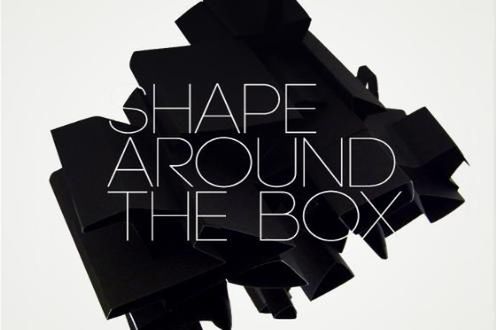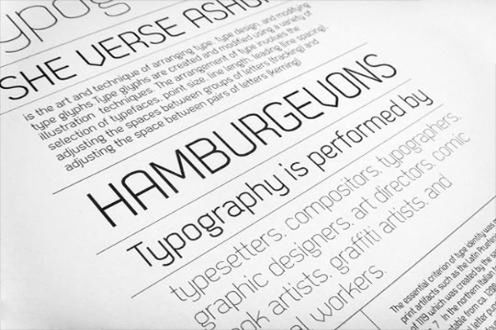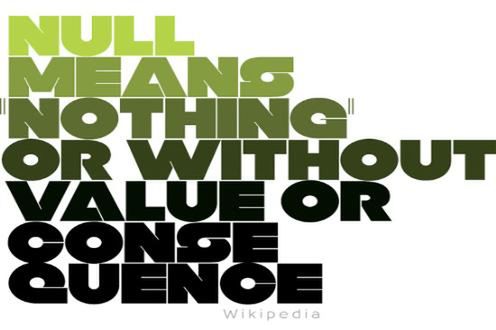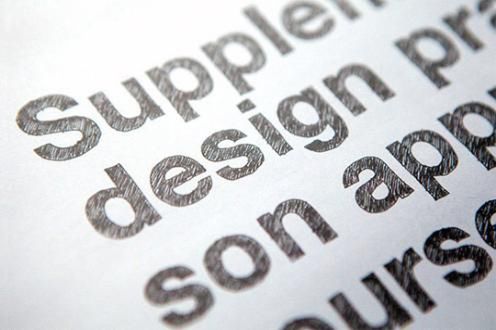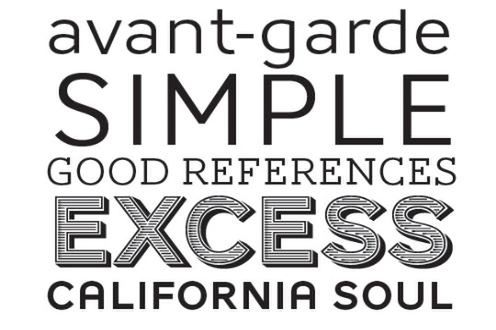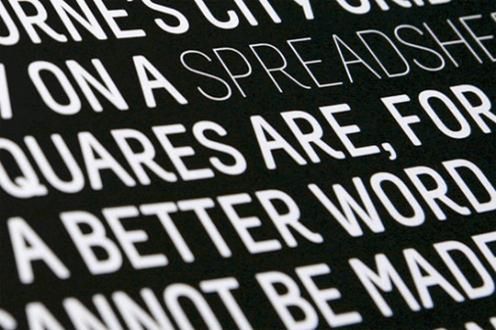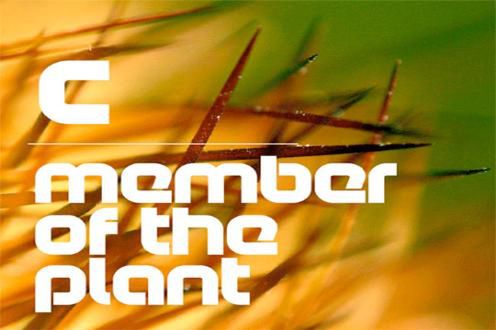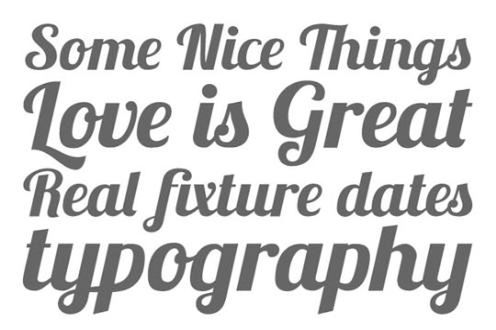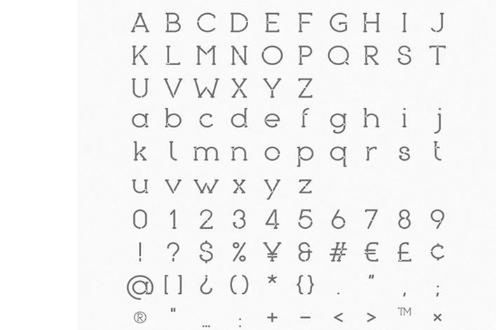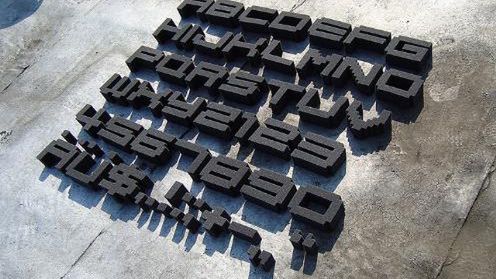
Najlepsze darmowe czcionki 2010 roku [TOP 10]
Wielkimi krokami zbliża się koniec roku. To tradycyjny czas podsumowań. Dziś prezentujemy Wam 10 darmowych czcionek okrzykniętych mianem najlepszych. Jakie trendy dominowały podczas ostatnich miesięcy?
Dekar
Ta czcionka świetnie sprawdza się we wszystkich projektach graficznych – na stronach WWW czy w korporacyjnych logotypach. Czcionka jest przeznaczona dla komputerów klasy PC i Mac. Dekar nie obsługuje polskich znaków diakrytycznych, ale za to jest dostępny za darmo ;). Do pobrania tutaj.
Sketchetik Light
Ta czcionka z pewnością ucieszy fanów wszystkiego, co kreślone ołówkiem. Można ją pobrać stąd.
The Lobster Font
Inspiracją do stworzenia tej czcionki był homar ;). Jeśli chcecie dorzucić swoje 3 grosze, autor czeka na Wasze sugestie i finansowe wsparcie ;). Wszystko na ten temat tutaj.
AW Conqueror
5 rodzajów ekskluzywnej czcionki zaprojektowanej przez Jean-Francoisa Porcheza oraz jeden chiński rodzaj stworzony przez Beijing Founder Electronics Co. ;). Do pobrania za darmo.
The Age Font
Age
Świetnie nadaje się do umieszczania na stronach internetowych lub plakatach. Czcionka zawiera 162 znaki, nie jest jednak przystosowana do pisania po polsku. Jest przeznaczona dla pecetów i komputerów klasy Mac. Dostępna tutaj.
Piron
Niepowtarzalna, niejednolita w swojej strukturze czcionka. Można nią cieszyć oko i pobrać za darmo ;).
VAL Stencil
Czcionka, z której można „budować” (pisać) jak z klocków ;). Jak używać tej czcionki? Prezentuje to ten tutorial. „Budować” można za darmo.
Null
Taka czcionka na koszulce na pewno będzie rzucała się w oczy. Przyciągać wzrok można 162 znakami, za darmo.
Melbourne
Jest to czcionka o bardzo nowoczesnym wyglądzie. W jej tworzeniu brał udział profesor Jovica Veljović z Wydziału Wzornictwa na HAW Hamburg. Do zobaczenia tutaj.
Code
Prosta, ale jednocześnie przyciągająca wzrok. Świetnie nadaje się do minimalistycznych wizytówek, plakatów itp. Do pobrania za darmo.